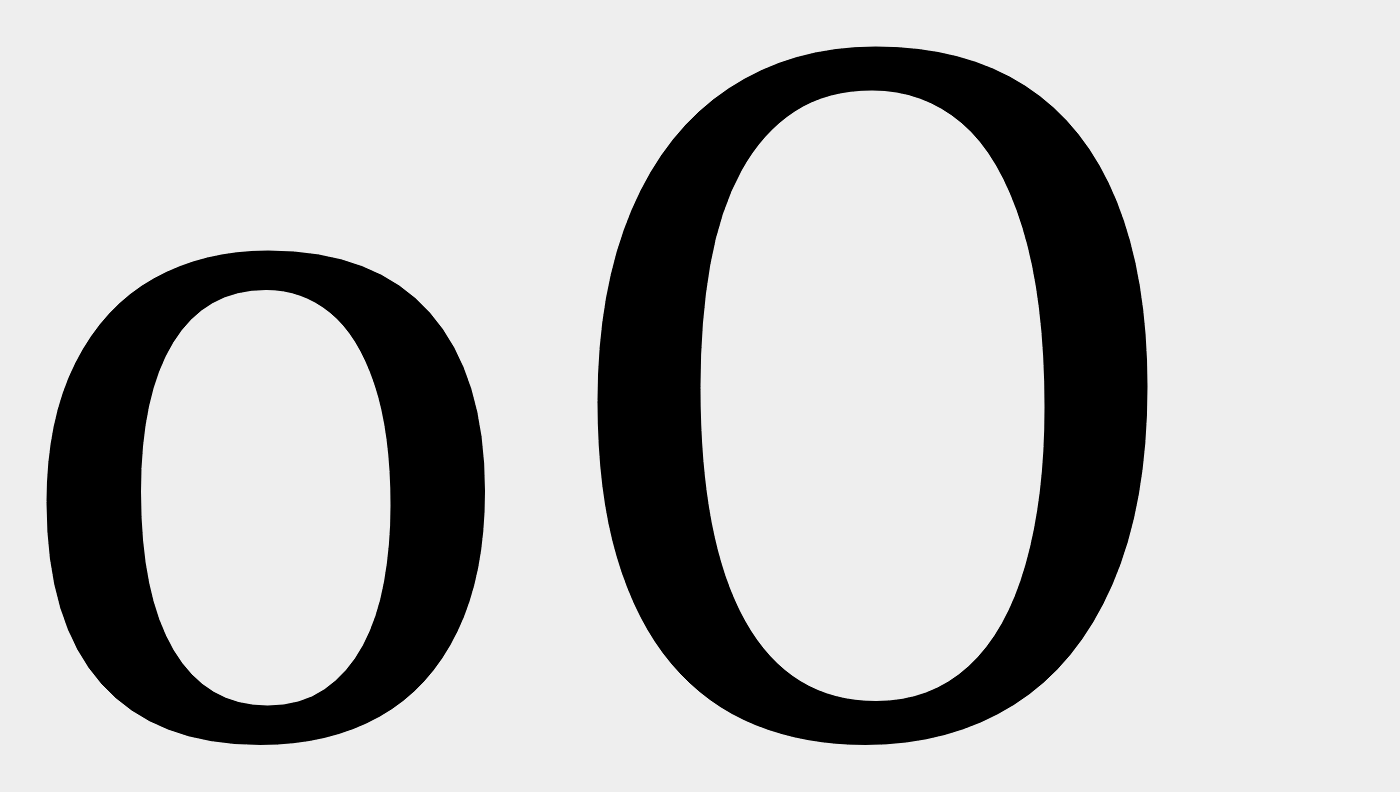
humanistisches, klassizistisches(statisches) Formprinzip
seit geraumer Zeit beschäftige ich mich mit dem Diskussions-Stand zur Schriftenklassifikation und der Position nach Formprinzip zu klassifizieren, was mir eigentlich sehr einleuchtet. Allerdings habe ich ab und zu so meine Probleme die entsprechenden Einordnungen nachzuvollziehen. Also lt. I. Kupferschmid in ihrem Buch "Buchstaben kommen selten allein", wird unterschieden zwischen dynamischem und statischem Formprinzip (was wohl weitgehend dem humanistischen bzw. klassizistischen Formprinzip entspricht). Jetzt sehe ich bspw. die Cambria auf dieser Webseite, die hier zum statischen Formprinzip gezählt wird. Aber mir scheint diese Schrift doch eher zu den Übergangs(Barock)-Antiquas zu gehören, die ein dynamisches Formprinzip aufweisen. Bei der Grundlinie ist der Federzug noch zu erkennen, die Buchstabenformen sind eher offen als geschlossen, die Kontrastachse ist leicht geneigt...?
Tja, so ist das mit den Klassifikationen. Es sind eben grobe Einteilungen und nicht nicht immer lassen sich Schriften klar in genau eine Schublade stecken. Die Cambria ist so ein Fall.
Schau dir mal die O/o an:
Die Schattenachse ist schon ziemlich aufrecht. Zum Vergleich eine klare humanistische Schrift:
Andere Details der Cambria mögen dagegen wieder eher humanistisch wirken …
ich frage mich eh wozu man dieses 'schubladendenken' benötigt.
ist doch völlig uninteressant ob eine schrift nun eine klassizistische antiqua ist oder eine barock-antiqua ist.
selbst im unterrricht finde ich es unnötig, denn es lassen sich nicht alle schriften darunter einorden und es wäre evtl. einfacher von einflüssen zu sprechen. serifenschrift mit klassizitischen einflüssen siehe unterschiede zw. haar- und grundstrich.
Das beruhigt mich, dass man da nicht immer so definitiv einordnet, dass man bei einer zweideutigen Schrift auch von humanistischen oder klassizistischen Einflüssen sprechen kann.